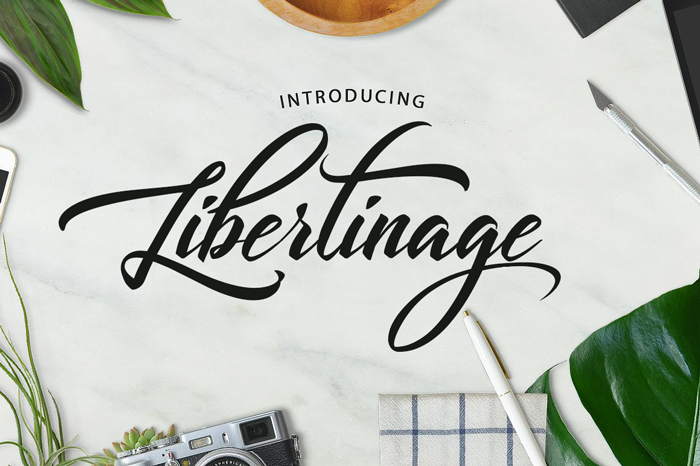
Aqui está uma descrição envolvente e natural para a página de download da font ‘Libertinage Script Font’, categorizada como Fonts de Escrita: Descubra Libertinage Script, uma fonte de escrita feita especialmente para atingir um equilíbrio harmonioso entre elegância e facilidade. Desenvolvida pelo Octotype, a Libertinage Script traz linhas suaves e curvas delicadas que se assemelham às obras de artes góticas. Seu design lembra o estilo da fonte francesa Libertine, cujas características incluem uma combinação única de elegância e naturalidade. Com seu formato completo e licença comercial, você pode experimentar a sensação única dessa escrita em seus projetos gráficos. A Libertinage Script é ideal para criar um texto que exalando personalidade enquanto mantém a sofisticação necessária nos materiais profissionais ou de design pessoal. Libertinage Script oferece uma maneira visualmente atraente e única para incorporar suas mensagens, criando um texto único e autêntico. Esta fonte é perfeita para designers gráficos que buscam adicionar um toque distintivo em seus projetos de escrita. Acessível através do , você pode experimentar Libertinage Script hoje, encontrando uma combinação única entre beleza e conforto no seu próximo projeto.
Designer: Octotype